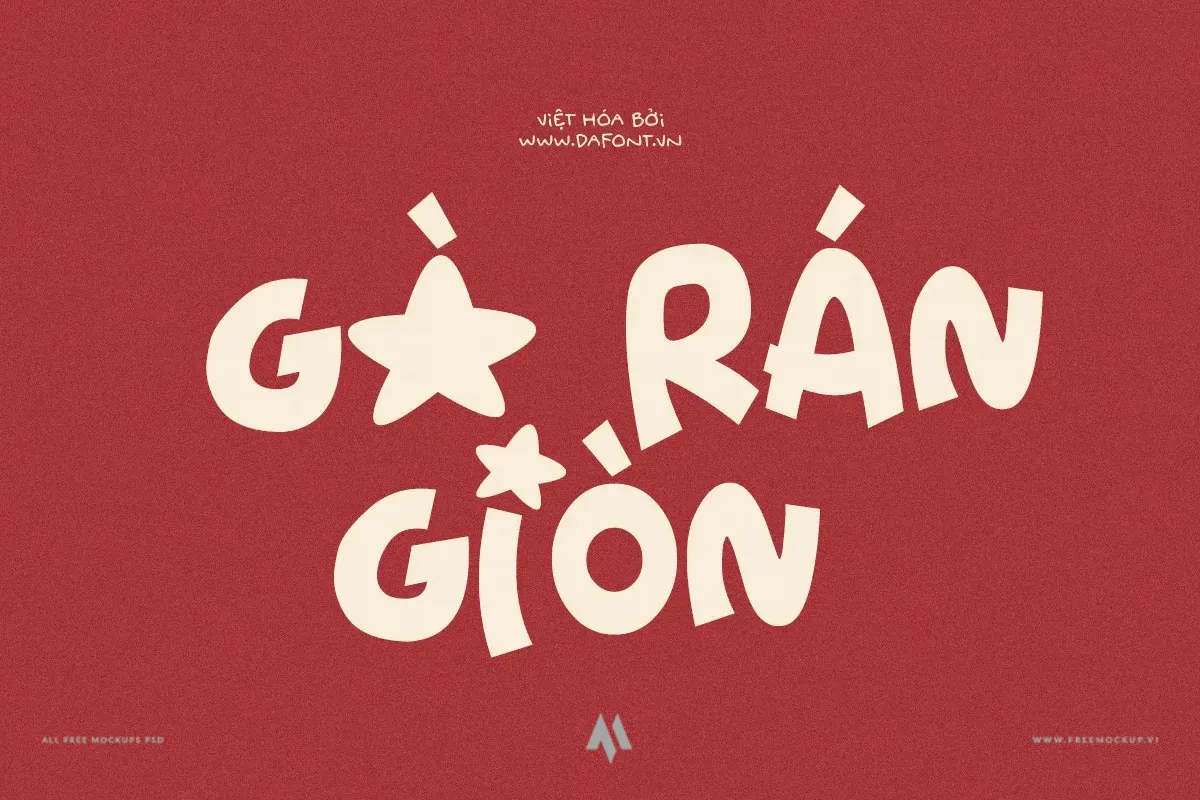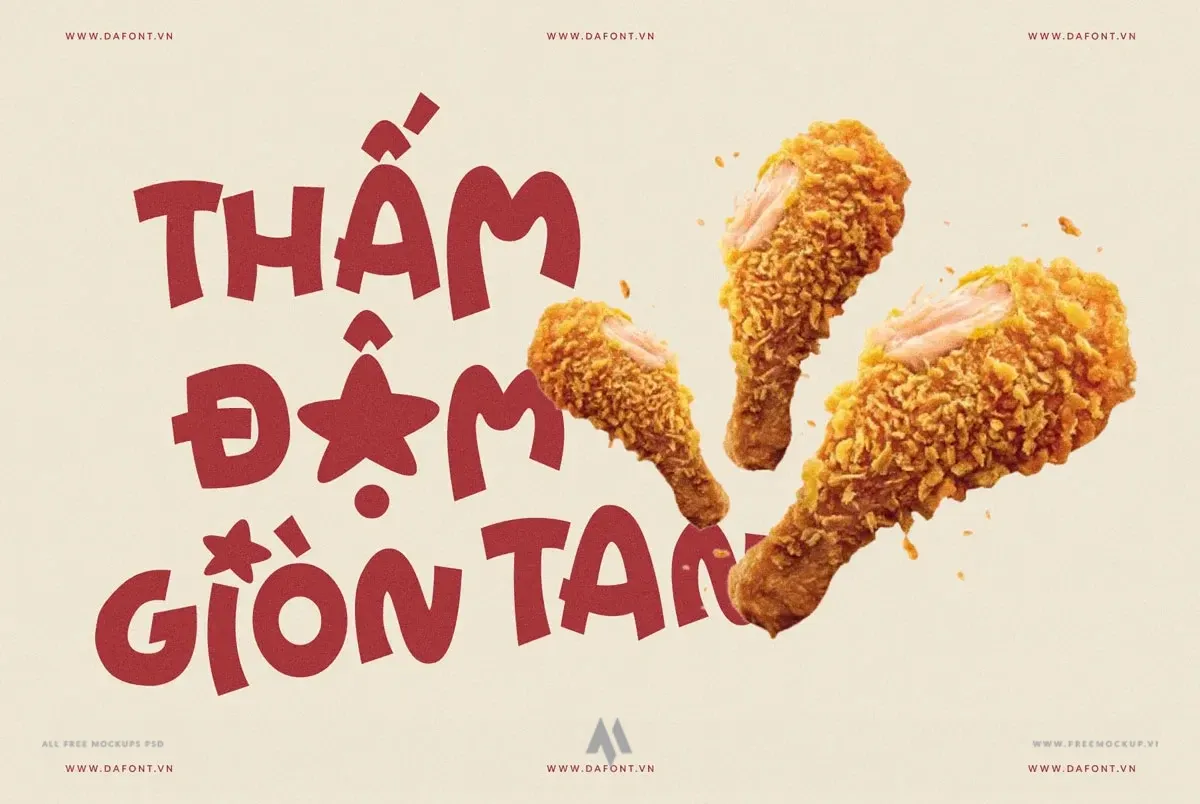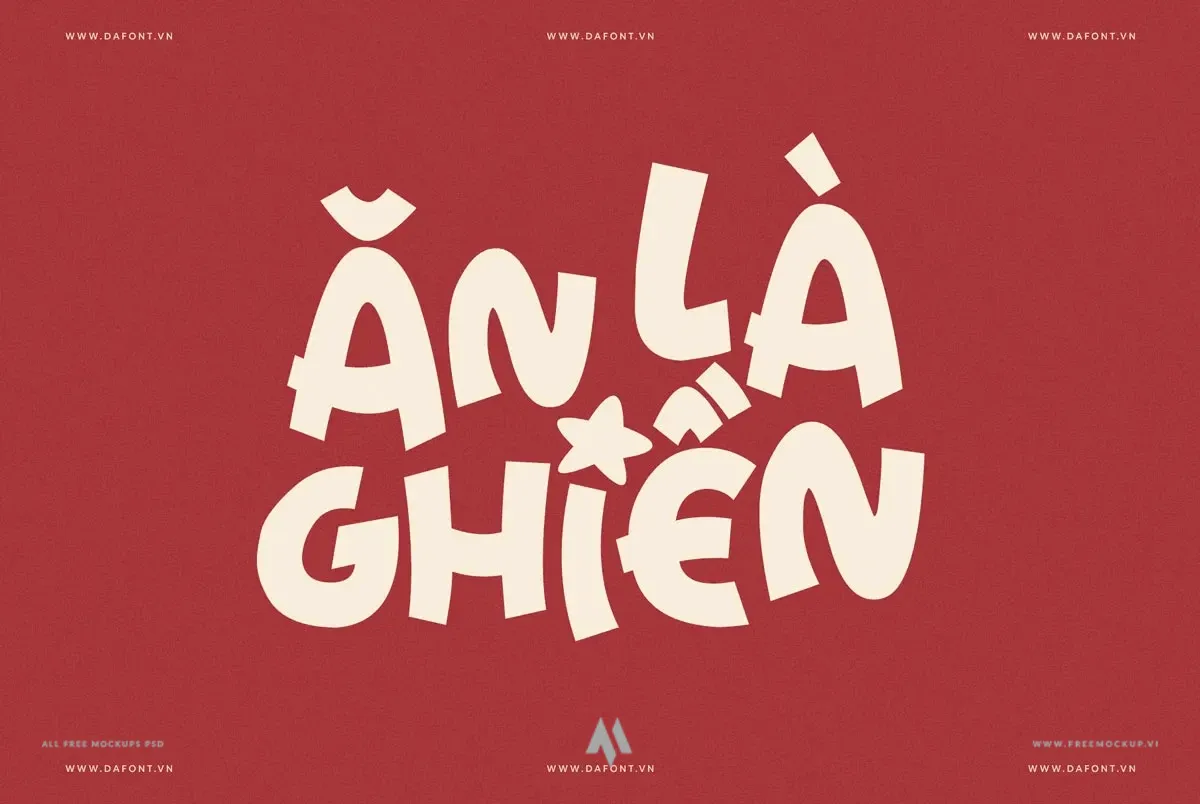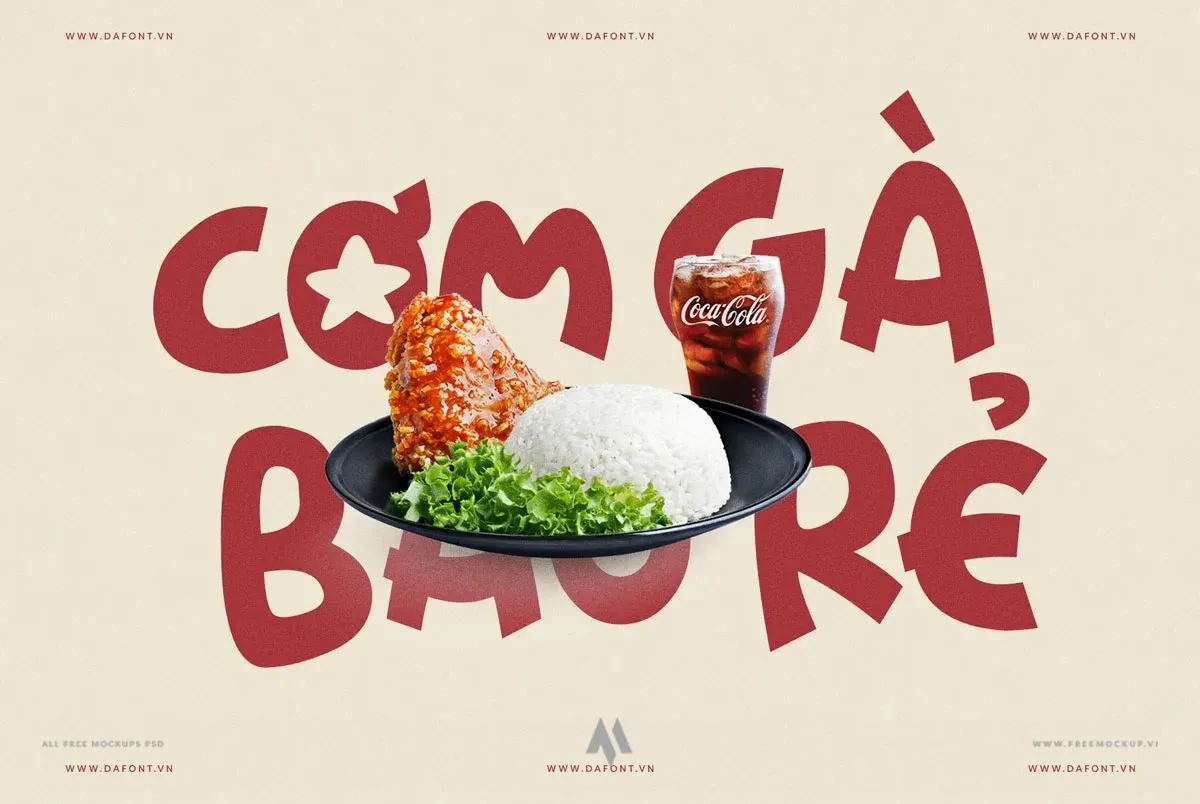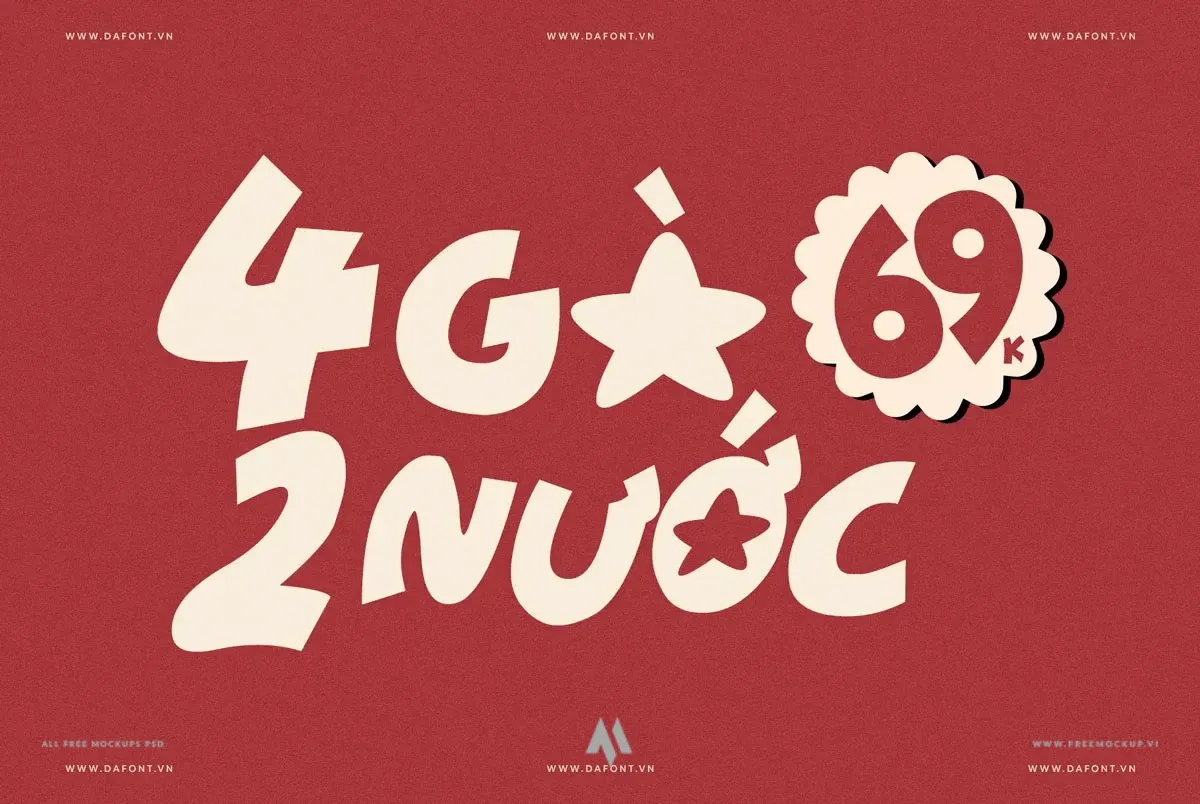
DFVN Starshines Việt Hóa là bộ font chữ serif mang phong cách kết hợp hoàn hảo giữa nét thanh lịch cổ điển và sự phóng khoáng, vui tươi hiện đại. Với cấu trúc vững chãi đan xen những đường cong uốn lượn tinh tế, bộ font mang đến điểm nhấn thị giác cuốn hút, sang trọng nhưng vẫn giữ được nét thân thiện, gần gũi cho mọi ấn phẩm.
Đặc điểm nổi bật
- Chi tiết cách điệu độc đáo: Các điểm nối, đỉnh chữ và nét gạch mảnh được trau chuốt nghệ thuật, tạo nên cá tính riêng biệt mà không làm mất đi tính cân đối tổng thể.
- Chân serif đối xứng chuẩn mực: Tạo nền tảng vững chắc, kết hợp khoảng cách chữ thoáng đãng giúp tối ưu khả năng đọc ở cả kích thước lớn lẫn vừa.
Ứng dụng đa dạng trong thiết kế
- Nhận diện thương hiệu: Thiết kế logo, typography cho các ngành hàng phong cách sống, mỹ phẩm, thời trang, quán cafe và studio nghệ thuật.
- Ấn phẩm xuất bản & Biên tập: Tiêu đề tạp chí, bìa sách, lookbook nghệ thuật và poster triển lãm.
- Bao bì & Nhãn mác: Tem nhãn sản phẩm thủ công cao cấp, bao bì thực phẩm, hộp quà tặng và thiệp mời trang trọng.
- Truyền thông số: Banner quảng bá, hình ảnh visual cho chiến dịch marketing và bài đăng mạng xã hội.